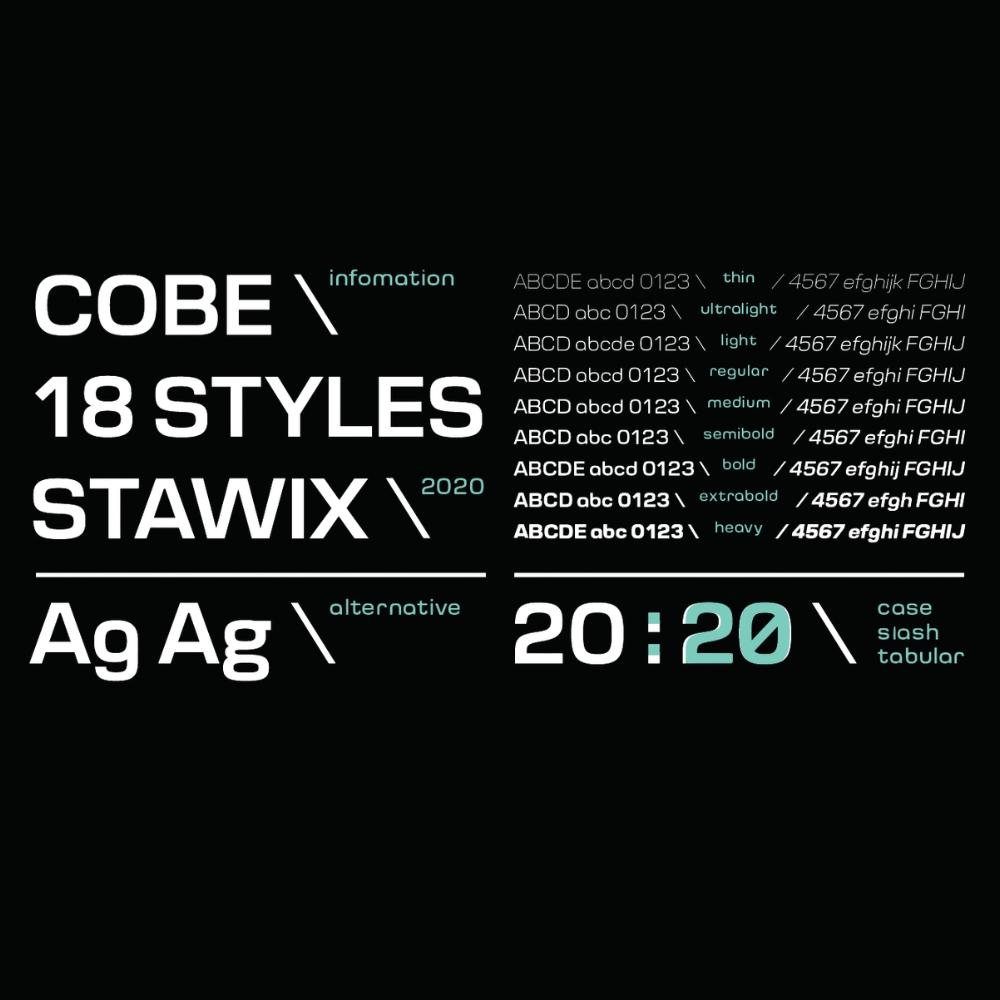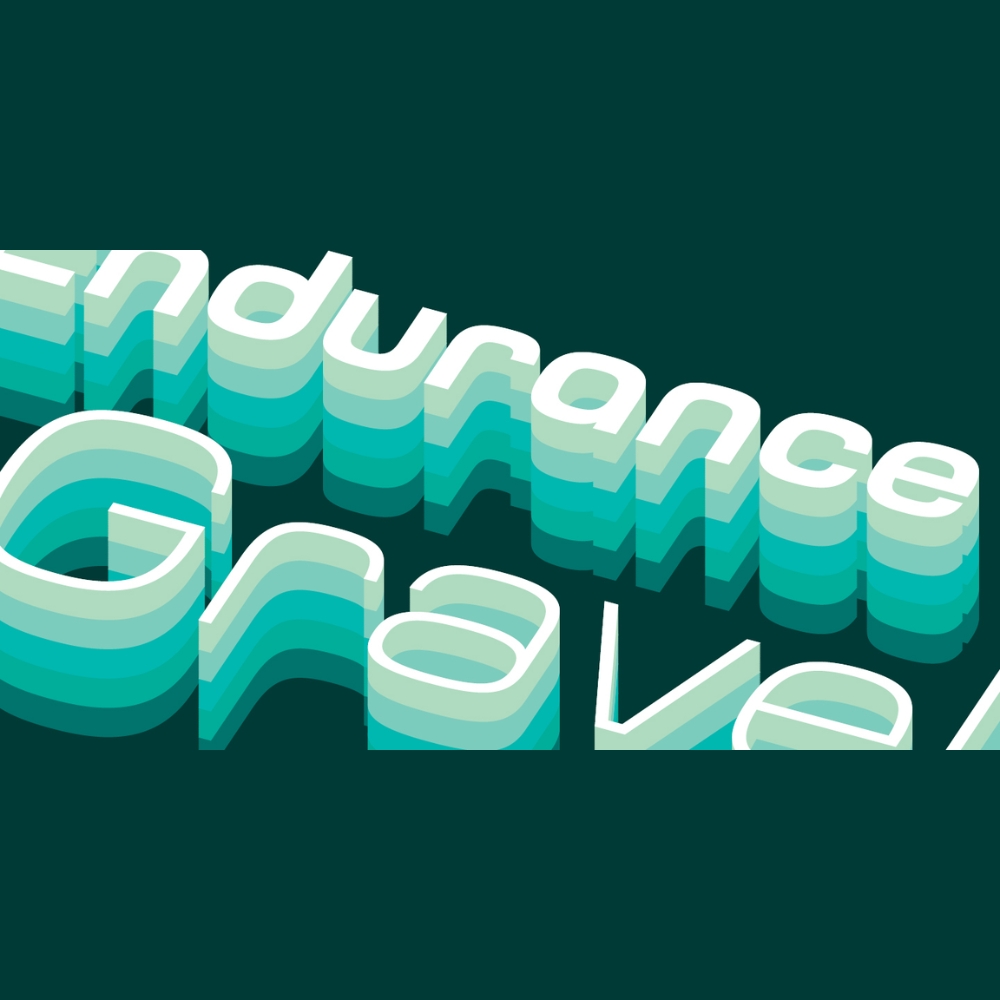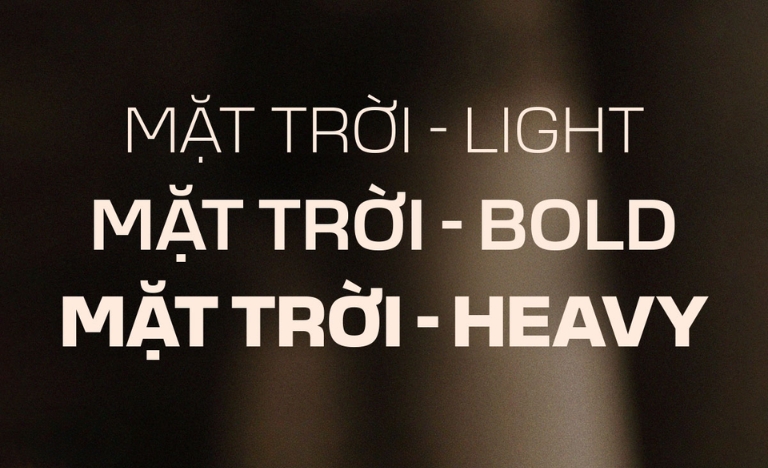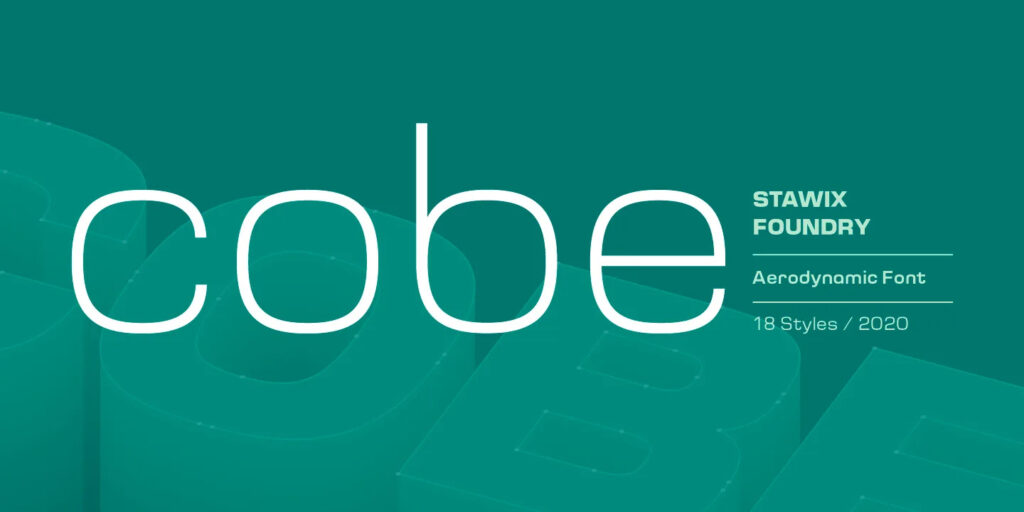
Cobe là một bộ font chữ thuộc dòng Sans Serif (không chân) mang phong cách hiện đại, gọn gàng và đầy tính chuyên nghiệp. Sự ra đời của phiên bản font Việt hóa Cobe đã mang đến một công cụ trình bày văn bản ổn định cho các nhà thiết kế và kiến trúc sư tại Việt Nam.
Khám phá những ưu điểm của bộ font Việt hóa Cobe
Dòng font này gây ấn tượng bởi cấu trúc hình học cân đối, các nét chữ có độ dày đồng nhất tạo nên cảm giác vững chãi và minh bạch. Font chữ tiếng Việt Cobe sans serif được đánh giá cao nhờ khả năng hiển thị rõ nét trên cả môi trường in ấn lẫn các thiết bị kỹ thuật số. Việc tối ưu hóa bộ dấu tiếng Việt giúp các ký tự như “đ, ă, ơ” hay các dấu thanh không bị lỗi hiển thị, giúp văn bản duy trì được sự tinh tế vốn có của bộ chữ gốc.
Bên cạnh đó, Cobe sở hữu vẻ đẹp tối giản nhưng không quá khô khan nhờ những đường bo góc nhẹ nhàng ở các ký tự. Đặc điểm này giúp font chữ phù hợp với xu hướng kiến trúc hiện đại, nơi sự gọn gàng và công năng luôn được đặt lên đầu tiên. Đây là phương án hiệu quả để trình bày các nội dung cần sự rõ ràng, dễ đọc nhưng vẫn thể hiện được gu thẩm mỹ hiện đại của người thiết kế.
Thông số kỹ thuật và tải font chữ tiếng Việt Cobe sans serif
| Phân loại phong cách | Sans Serif (Không chân) / Modern |
| Khả năng hiển thị | Ổn định trên web, in ấn, CAD |
| Mục đích phù hợp | Nội dung văn bản, hồ sơ kỹ thuật, Branding |
Gợi ý phối hợp: Font Cobe Sans Serif thường phát huy hiệu quả thị giác cao khi được sử dụng cho phần nội dung chi tiết hoặc thuyết minh dự án. Bạn có thể kết hợp nó với một font Serif có chân để làm tiêu đề nếu muốn tạo ra sự tương phản giữa nét cổ điển và hiện đại trong bố cục.
03 Ứng dụng thực tế của font Cobe trong ngành kiến trúc – xây dựng
Với vẻ ngoài chuyên nghiệp và hiện đại, bộ font này mang lại giá trị thực tế cao khi được ứng dụng vào các khâu vận hành và quảng bá công trình:
- Trình bày hồ sơ bản vẽ kỹ thuật: Các ghi chú về kích thước, vật liệu panel cách nhiệt hay kết cấu thép sẽ trở nên rõ ràng và dễ tra cứu hơn khi sử dụng font Cobe. Điều này giúp giảm thiểu sai sót cho đội ngũ thi công tại hiện trường.
- Thiết kế bộ nhận diện thương hiệu: Cobe là lựa chọn phù hợp để làm font chữ chủ đạo cho các công ty xây dựng, đơn vị thi công homestay nhờ sự vững chãi và chuyên nghiệp mà bộ font này mang lại.
- Giao diện website và ứng dụng: Đối với các doanh nghiệp kinh doanh nhà lắp ghép, việc sử dụng font Cobe trên website giúp nâng cao trải nghiệm người dùng, giúp khách hàng dễ dàng nắm bắt các thông số kỹ thuật và báo giá.
03 Lưu ý kỹ thuật khi trình bày văn bản với font Cobe
Để khai thác hiệu quả vẻ đẹp của font chữ tiếng Việt Cobe sans serif mà không làm rối mắt người xem, người thiết kế nên lưu tâm một số kinh nghiệm sau:
- Kiểm soát độ đậm (Font Weight): Cobe thường có nhiều cấp độ từ Light đến Bold. Bạn nên sử dụng các kiểu Regular hoặc Medium cho phần văn bản dài để đảm bảo tính dễ đọc và dùng kiểu Bold cho các đề mục quan trọng.
- Cân đối khoảng cách dòng (Leading): Do cấu trúc chữ Sans Serif có xu hướng dàn ngang, bạn nên nới rộng khoảng cách dòng một chút để văn bản trông thông thoáng, tránh cảm giác bết dính khi hiển thị ở kích thước nhỏ.
- Kiểm tra hiển thị trên thiết bị di động: Nếu dùng cho nội dung số, hãy kiểm tra khả năng hiển thị của font Cobe trên màn hình điện thoại để chắc chắn các dấu tiếng Việt không bị quá nhỏ hoặc khó nhận diện.